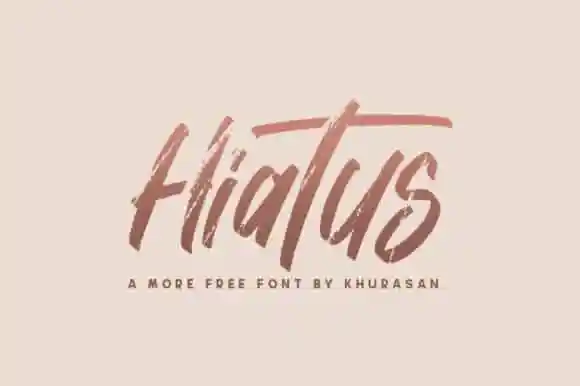
Hiatus Brush Font – Download Grátis
A fonte ‘Hiatus Brush Font’ é uma elegante caligrafia francesa que captura a sensação casual e rápida do desenho manual. Inspirada pela autenticidade dos traços de pincel, foi criada pelo designer Khurasan e caracterizada pelos movimentos sutis das marcas sobre o papel. Este script é perfeito para aplicar em logotipos ou como uma base de design, tornando qualquer obra de arte mais atraente e original. Suas letras estão pensadas com detalhes que refletem o estilo autêntico da caligrafia francesa, garantindo um toque único e único. Perfeito para criar designs modernos ou vintage, essa font oferece uma aparição única e criativa. O Hiatus Brush Font é perfeito tanto para uso isolado quanto em combinação com outras fonts, tornando-o uma opção valiosa para qualquer projeto de design.